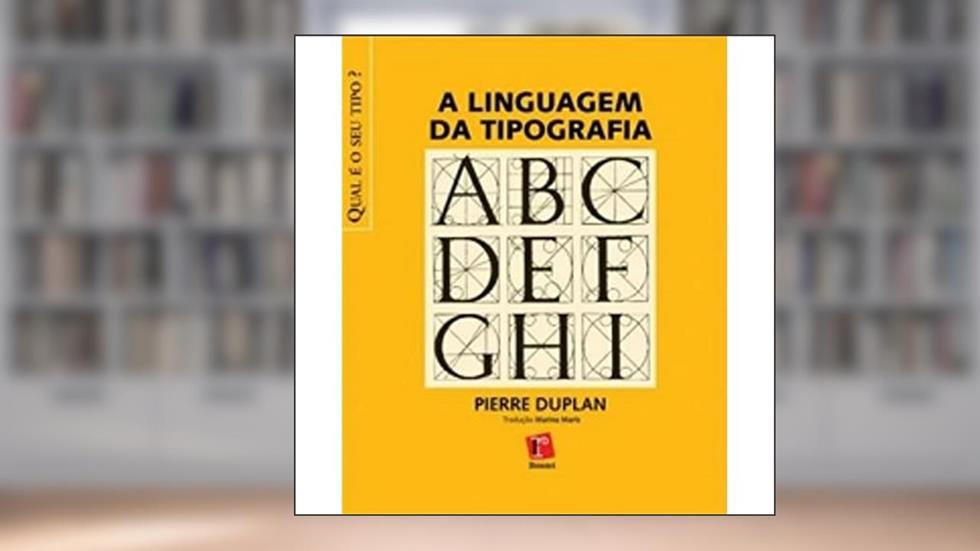
A tipografia é uma arte muitas vezes relegada ao segundo plano, mas em A Linguagem da Tipografia, Pierre Duplan explode essa concepção ao transformar o que poderia ser um mero manual técnico em uma experiência visual e emocional. Aqui, não se trata apenas de letras e fontes; a tipografia é a batida do coração de qualquer comunicação visual. 📢
Cada página deste livro é um convite à reflexão e ao deleite. Ao deslizar os olhos por suas linhas, você não apenas absorve conhecimento, mas também é convidado a sentir a dança das letras e a forma como elas dialogam umas com as outras, criando significados e interpretações que vão além do óbvio. É uma jornada que ressoa profundamente com todos nós, já que a comunicação acontece constantemente em nossas vidas. A escolha de uma fonte não é apenas estética; é uma decisão que pode mudar o impacto de uma mensagem.
Duplan, com sua prosa instigante, revela o poder escondido nas formas e espaços entre as palavras. Sua abordagem técnica é entremeada por reflexões sobre o impacto histórico da tipografia, desde os primórdios da impressão até a era digital, onde cada escolha é amplificada, influenciando nosso dia a dia de maneiras que muitos ignoram. Você já parou para pensar em como essa escolha pode emocionar, persuadir ou até mesmo manipular? O livro te traz essa consciência, como um despertar que faz você questionar tudo que conhece sobre a comunicação visual.
Os comentários dos leitores sobre essa obra são um misto de admiração e descoberta. Muitos destacam a capacidade de Duplan de transformar um tema aparentemente seco em algo vibrante e cativante. Há quem afirme que, após a leitura, se sentem como verdadeiros artistas da tipografia, prontos para aplicar novos conhecimentos em projetos pessoais ou profissionais. Outros, por sua vez, criticam a profundidade técnica, argumentando que o livro poderia ter se aprofundado mais em exemplos práticos. Contudo, é exatamente essa provocação que instiga debates e reflexões.
Com uma visão crítica e um olhar atento, Duplan ilustra não apenas a evolução da tipografia, mas também como ela reflete e molda a sociedade. Pense em como as letras que vemos diariamente nas redes sociais, em outdoors e até em rótulos de produtos não fazem parte do mesmo universo mágico que ele desenha. As fontes que escolhemos são atordoadoras, capazes de gerar emoções profundas e até mesmo alterações de comportamento. Isso é tipografia falando, isso é comunicação em ação.
Ao final da leitura, não são apenas os conhecimentos que você adquire; é a transformação que acontece dentro de você ao perceber que cada letra carrega consigo uma história, um sentimento, e poder. A Linguagem da Tipografia é mais que um livro; é uma ode à arte da comunicação que nos empodera, nos faz ver além e nos convida a nos expressar de forma consciente e intencional. Se você ainda não se deixou levar por essa encantadora montanha-russa tipográfica, não perca mais tempo. A sua jornada na fascinante linguagem da tipografia está prestes a começar! ✨️